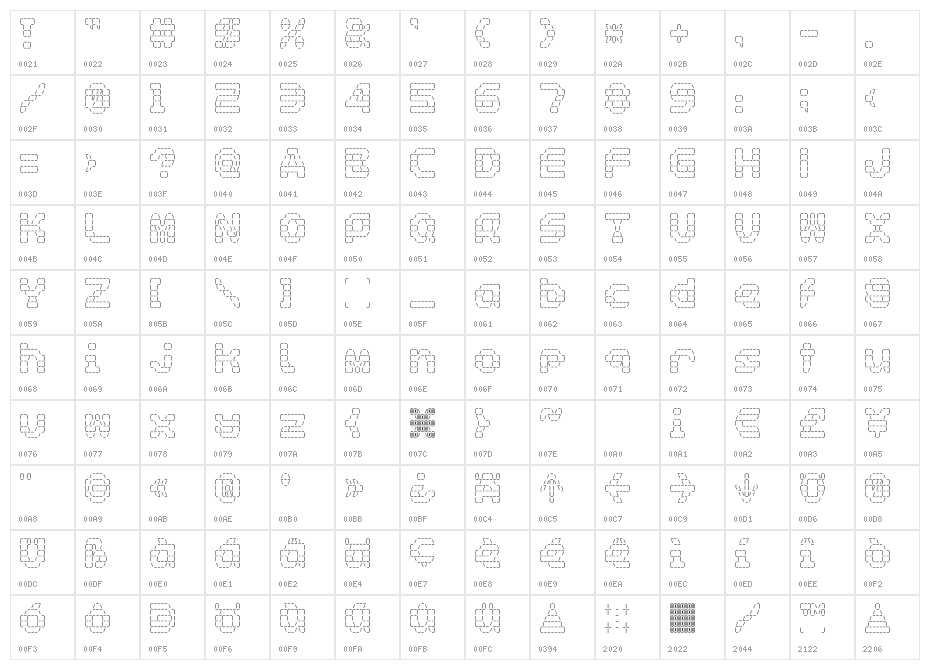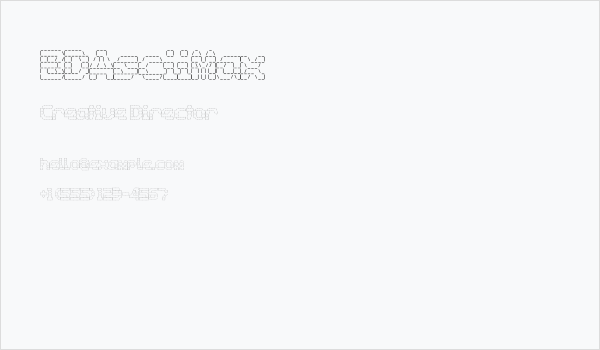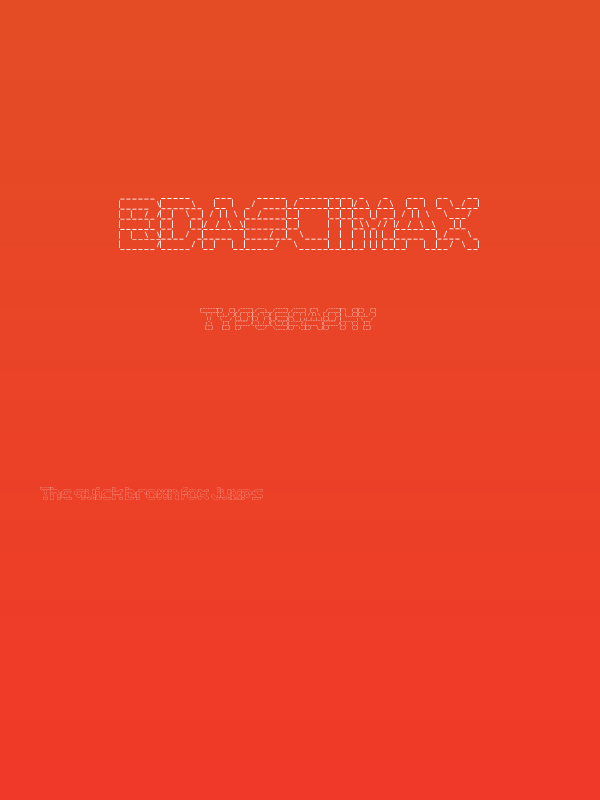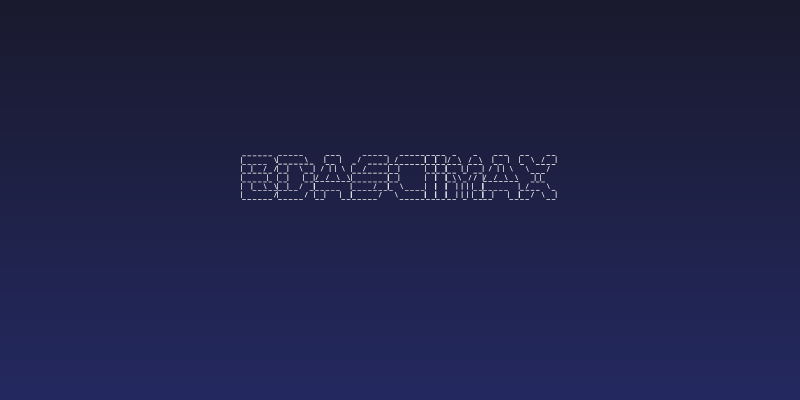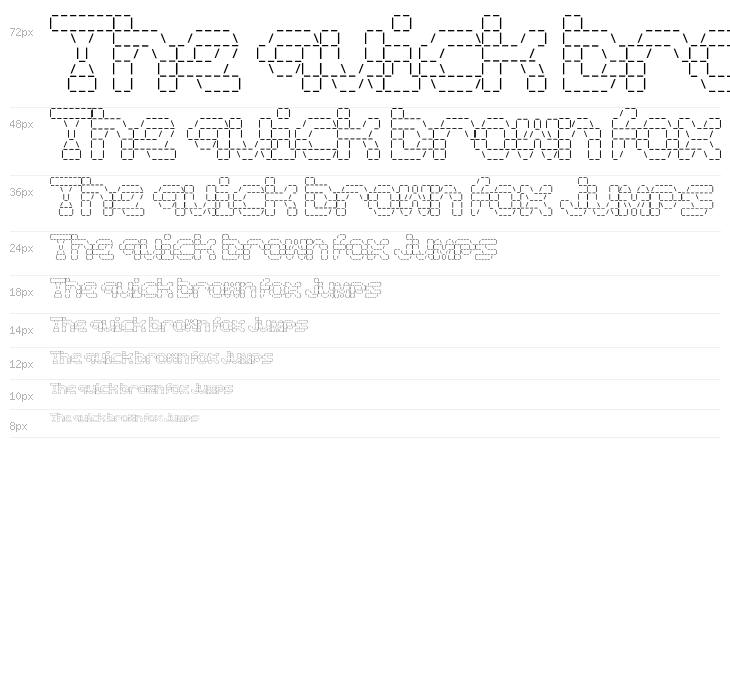
BDAsciiMax Font
| Categorie | Typewriter |
| Stile generale | Retro, Digital |
| Caso d'uso | Logos, Art projects, Themed designs |
| Progetti proposti | Ideal for retro-themed designs, digital art projects, or any creative work that requires a nostalgic, computer-era aesthetic. |